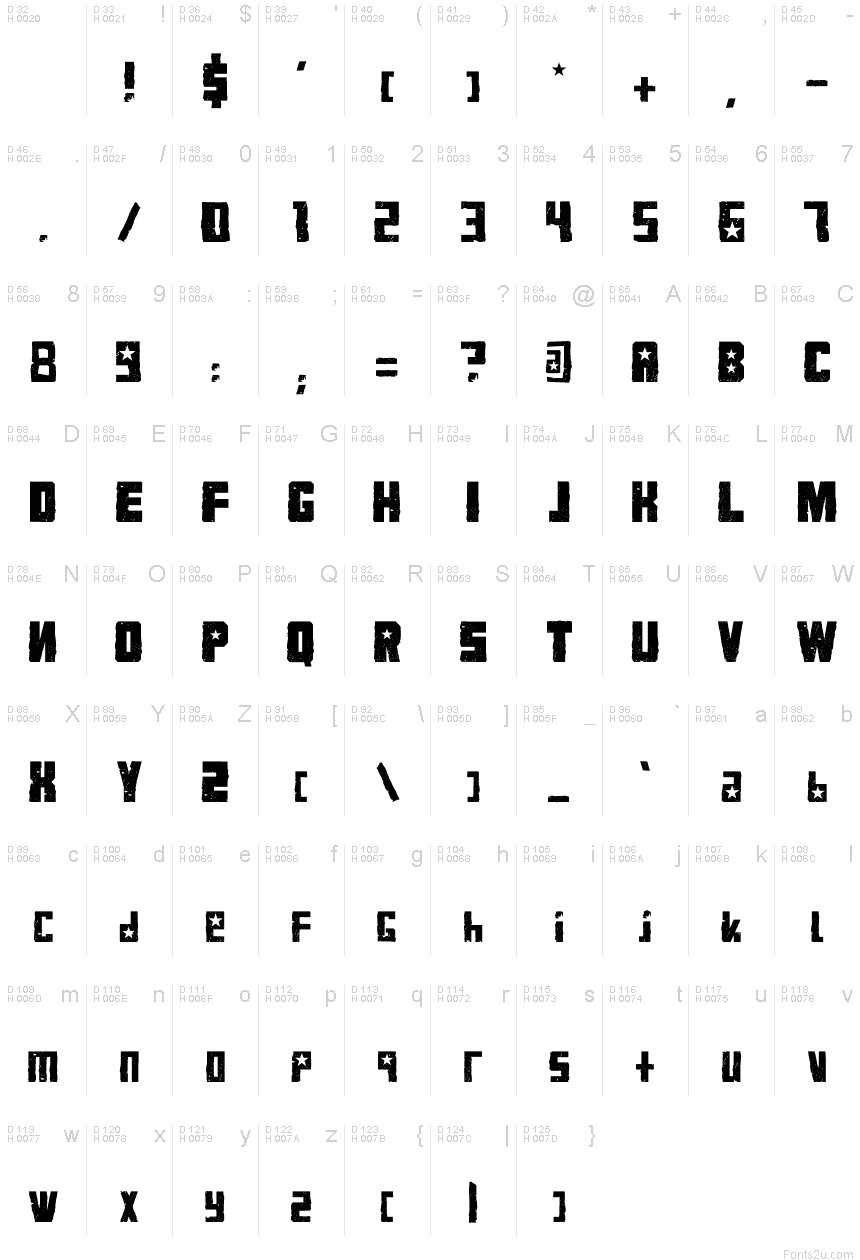
KonQa Black od Victorius Graphics to darmowy, postarzany krój typu display, który wygląda, jakby został przeciągnięty po betonie i ponownie oczyszczony. Kanciaste, surowe formy ścierają się tu z wyszczerbieniami, piaskowymi plamkami i wyrazistym wycięciem w kształcie gwiazdy, co nadaje KonQa bezkompromisową, miejską energię, która pozostaje czytelna nawet z daleka. Efekt to głośna, wyrazista typografia, która przywodzi na myśl napisy na zardzewiałym metalu lub szablony na drzwiach magazynów.
Używając KonQa Black, Twoje nagłówki uderzają niczym logo wbite w skrzynie – są surowe, zniszczone i niemożliwe do zignorowania. Ten darmowy font świetnie sprawdzi się na plakatach koncertowych, w brandingu sportów ekstremalnych, tytułach gier, na odzieży streetwearowej, w grafikach do horrorów czy filmów akcji oraz w odważnych materiałach promocyjnych w mediach społecznościowych. Aby zachować równowagę, połącz KonQa z prostym, bezszeryfowym krojem w tekście głównym i używaj KonQa w dużym formacie: najlepiej prezentuje się w przerośniętych nagłówkach oraz krótkich, mocnych hasłach.